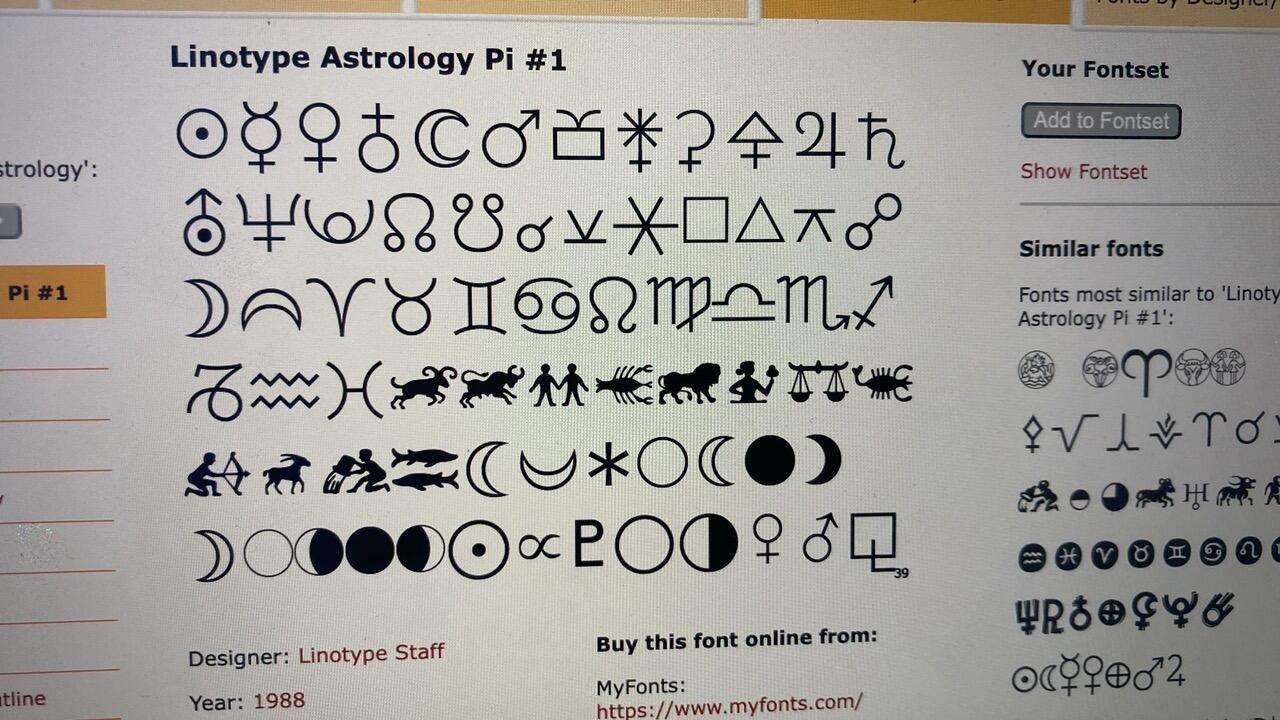
Suche nach einem Schriftsatz mit allen astronomischen Zeichen
Leider hat Adobe den Schriftsatz «Linotype Astrology Pi #1» von heute auf morgen aus dem Verkehr gezogen. Für die Erstellung des Magazins ORION der Schweizerischen Astronomischen Gesellschaft war dieser Schriftsatz praktisch unabdingbar, da er alle benötigten astronomischen Zeichen enthielt.
Kennt jemand einen entsprechenden Ersatz?
Die Icons von David Lawrences »Rosart & Fleisch« (California Type Foundry) sind in puncto Astro-Symbole recht umfassend ausgebaut. Es ist natürlich ein anderer Stil.